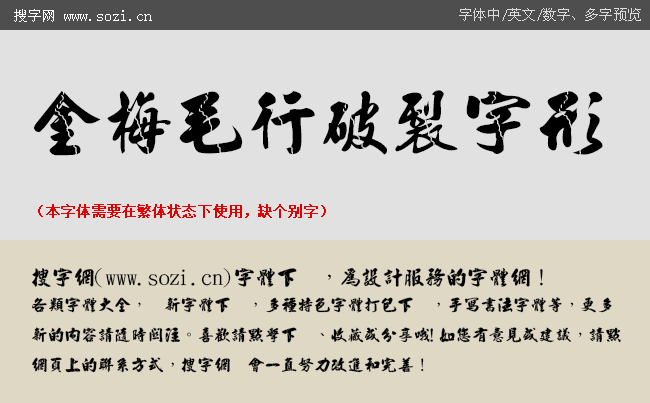
金梅毛行破裂字形
搜字網(wǎng)提供一款個(gè)性化的書法字體金梅毛行破裂字形下載,這是一款非常帶有破裂效果的手寫書法字體,具有毛筆字的書法風(fēng)格,并具有裂紋的個(gè)性化,適用于樣本畫冊,報(bào)紙排版,網(wǎng)頁標(biāo)題等廣告設(shè)計(jì)應(yīng)用。